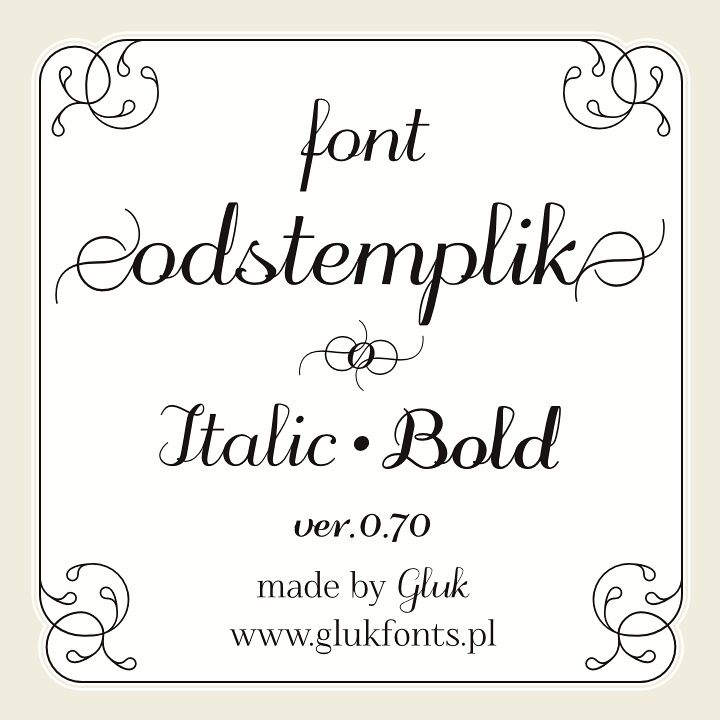
Odstemplik by gluk ist eine kostenlose, kontrastreiche Schreibschrift mit einer selbstbewussten, modeorientierten Note. Ihre ausladenden Kurven und die steile Neigung erinnern an schnelles Handlettering mit der Feder, akzentuiert durch lange aufrechte Striche. Feine Verbindungen lassen die Formen leicht und fließend wirken.
Boutiquen für Mode oder Kosmetik könnten sie für Verpackungen und Kampagnengrafiken einsetzen, bei denen die elegante Bewegung zu einem edlen Image passt. Sie besitzt zudem die nötige Intimität für Hochzeitseinladungen. Am überzeugendsten wirkt die Schrift als Produktname oder signaturähnliche Wortmarke.
odstemplik